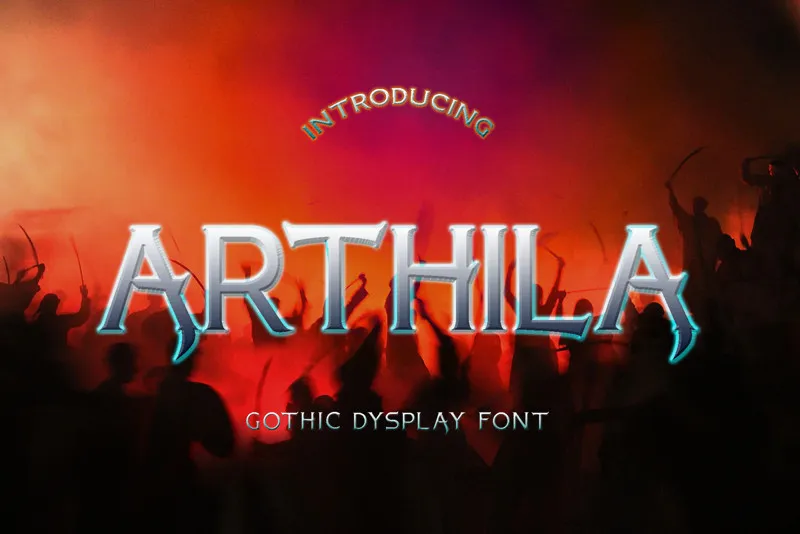
ARTHILA Display Font – Fonte Grátis
ARTHILA Display Font
A ARTHILA Display Font foi inspirada nos fonts serif e do período romano, conhecidos por suas letras fortes, afiladas e limpas. Esta fonte é perfeita para projetos de logotipo e outras necessidades de design, proporcionando um toque único e poderoso aos seus trabalhos. Se você quiser saber mais sobre esta fonte ou outras opções que oferecemos, deixe seu comentário ou mensagem e faremos o possível para esclarecer suas dúvidas. Tanto os designers quanto os amantes da arte podem apreciar a elegância e o impacto desta fonte no design de seus projetos.